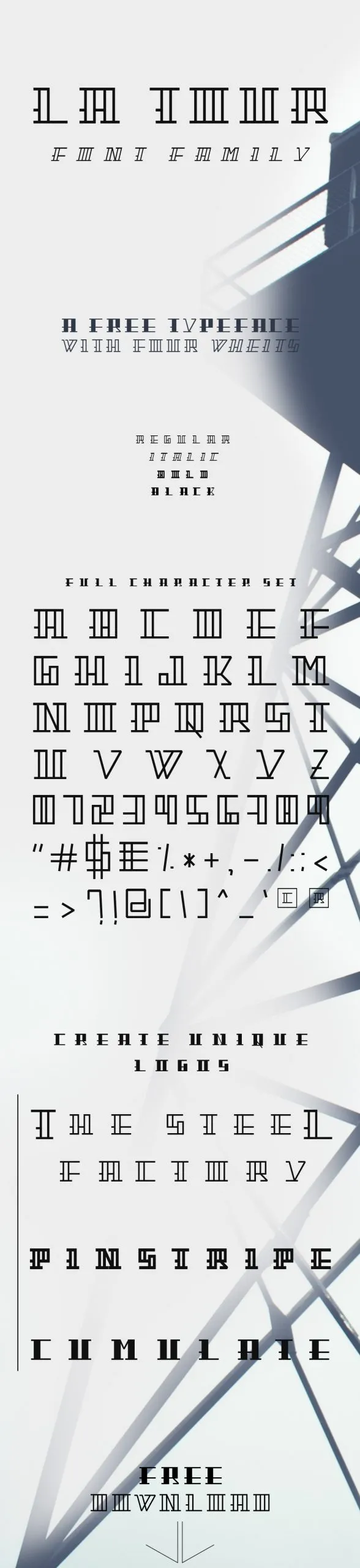
La Tour Font – Download Grátis
La Tour Font é uma nova tipografia projetada pela Wood Studio para uso pessoal e comercial gratuito. Esta elegante família serif oferece linhas sólidas e cânulas finas que contribuem para um design de texto impecável. É especialmente apropriado para ambientes onde uma aparência sóbria e sofisticada são desejadas, seja em editoriais de jornais ou em publicações online. Como designer independente, Hamilton criou La Tour Font com cuidado para garantir que as linhas da fonte sejam perfeitamente ajustadas, proporcionando um texto fluido e legível para qualquer aplicação visual. Essa fonte é uma ótima opção para quem busca uma mistura de elegância clássica e modernidade sofisticada. Experimente La Tour Font e compartilhe suas impressões conosco.